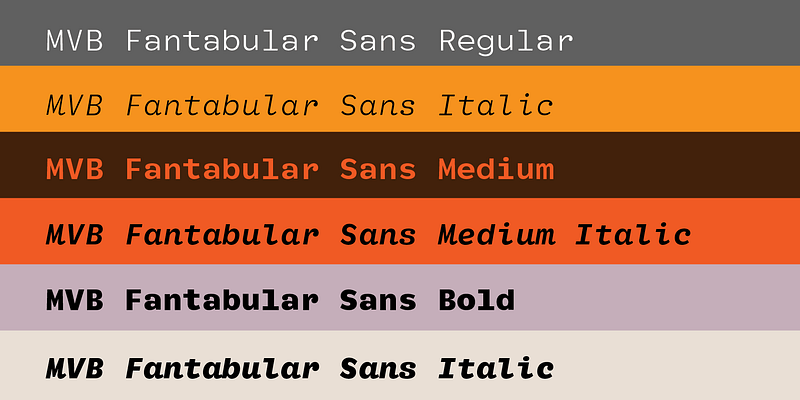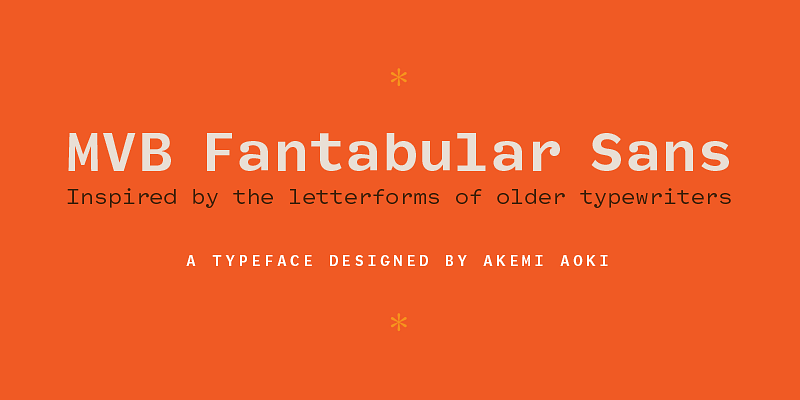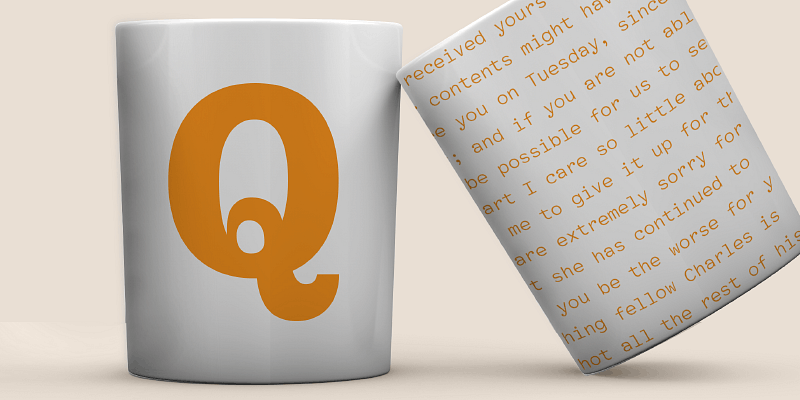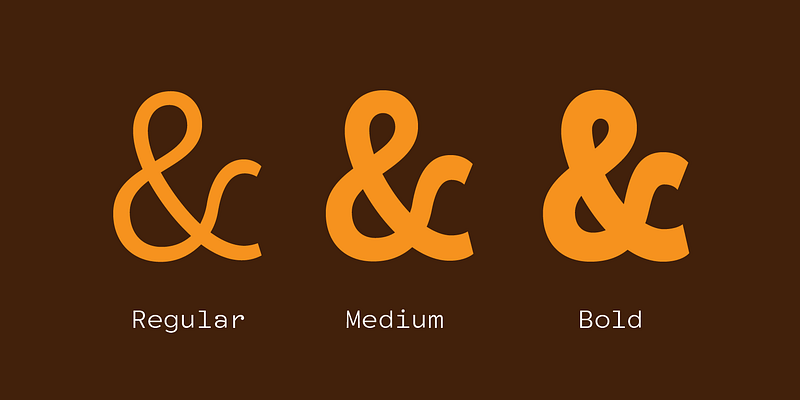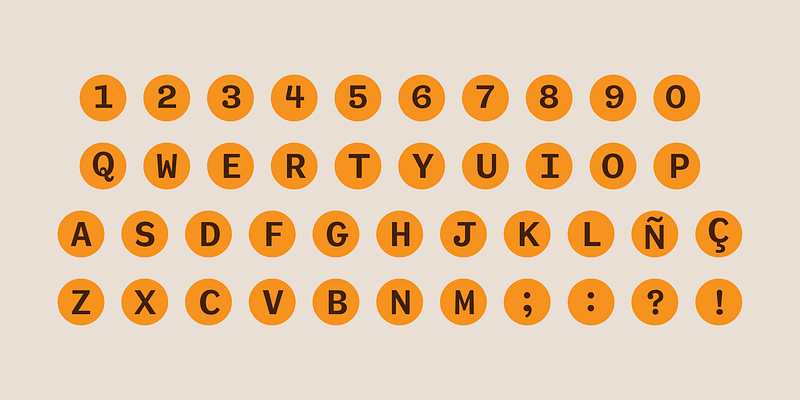
「MVB Fantabular」を見ると、等幅フォントはかしこまった、味気のないフォントである必要がないということが分かります。Akemi Aoki は、昔のタイプライターの文字に着想を得て、イタリックを使った 3 つのウェイトを持つ遊び心のあるファミリーフォントをデザインしました。どの文字でも同じ幅の「MVB Fantabular」は、等幅フォントが必要な所にはどこでも使えますが、書体は非常にゆったりしていて屈託がなく、等幅フォントであることを気づかせず、他の設定でも使用することができます。MVB Fantabular Sans は、MVB Fantabular のサンセリフ体のバージョンです。